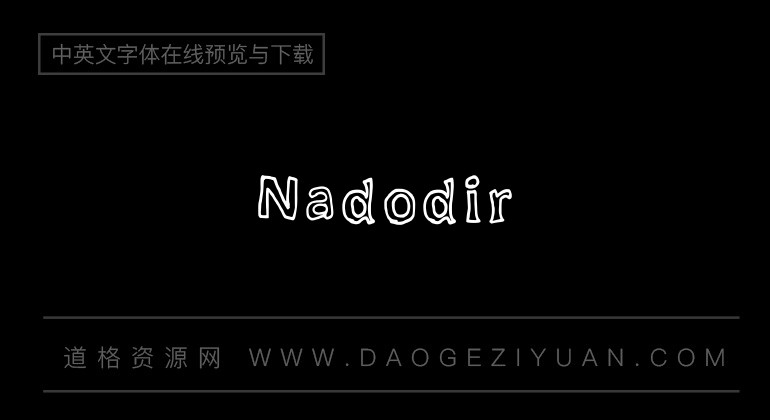
Nadodir字体是一款由印度设计师Saurabh Datar设计的非常精美的字体,它的特点是具有精致的外观,优雅的曲线,清晰的笔画,以及极具穿透力的多种字体风格。Nadodir字体可以应用于广告,标志,标题,书籍,报纸,海报等等,为设计师提供了丰富的设计空间。内容介绍
Nadodir是一款非常不错的手写艺术字体,具有很好的视觉感,适合于文化类的宣传设计、商业类品牌的广告和产品包装设计以及个性化文字排版等较多场景。